月刊MdN 2017年10月号(特集:絶対フォント感を身につける。[明朝体編])
月刊MdNで、2015年から年1回程のペースで特集されている『絶対フォント感を身につける。』。の第3弾特集号が9月に発売になった。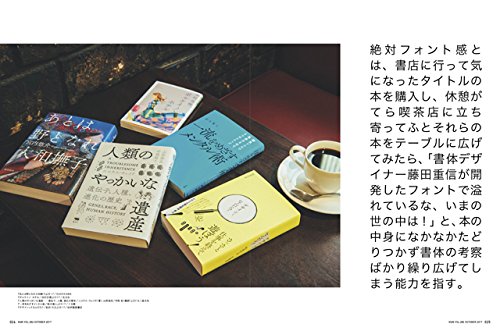
絶対フォント感
文字を見ただけでその書体を言い当てられる能力を指している。
また書店に行って気になったタイトルの本を購入し、休憩がてら喫茶店に立ち寄ってふとそれらの本をテーブルに広げてみたら、「書体デザイナー藤田重信が開発したフォントで溢れているな、いまの世の中は!」と、本の中身になかなかたどりつかず書体の考察ばかり繰り広げてしまう能力を指していたり、端正なフォルムと情感ある墨溜まりで文字好きだったら思わず惹かれてしまう「A1明朝」で組まれたキャッチコピーを見て、そのフェティッシュな書体と言葉の両方からいま映画館で体験できる美しいストーリーと映像を勝手に想像して涙ぐんでしまう能力を指すようだ。いま映画館で体験できるその映画のストーリーに関してはあまり良い評判を聞かないが、果たしてフォントとキャッチコピーだけで涙ぐめるのだろうか。
それはさておき、9月6日に発売された月刊MdN10月号では、一年ぶりに「絶対フォント感を身につける。」が特集され、今回の特集で第3弾となる絶対フォント感を身につける。シリーズでは「明朝体編」がクローズアップされた。
明朝体は縦画が太く横画が細い、また終筆の終わりにうろこがあり、楷書の特徴を残しているといった特徴がある書体。
明朝体編表紙
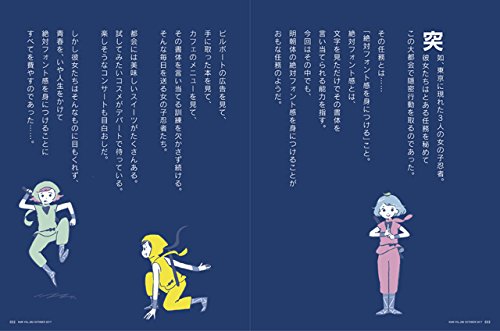
突如、東京に現れた3人の女の子忍者。その任務は「絶対フォント感を身につける」こと。
明朝体の基礎を知る
明朝体の「漢字」は工業製品のような機能美を持っている。これは横画の終筆部分の三角形のうろこの部位など、明朝体におけるフォーマッタブルな部分を説明しての解釈。
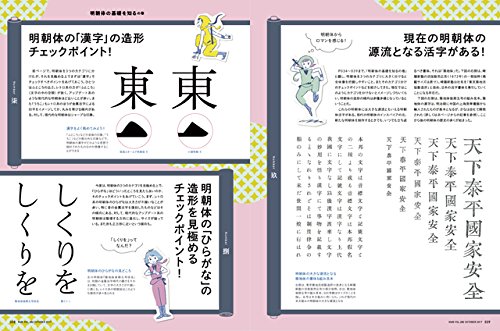
明朝体の「ひらがな」は漢字に比べて体臭がある。漢字に比べて、筆で書かれたような工業化されきっていない部分を説明した文。
游明朝体 Mのはらい
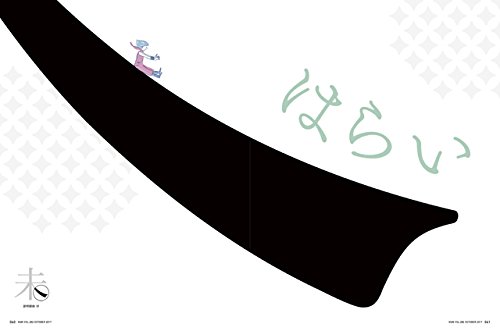
はらいで見開きを使うという贅沢すぎるページ構成。
明朝体の歴史のはじまり。――誰がつくったのか、どう発展したのか
講師:小宮山博史
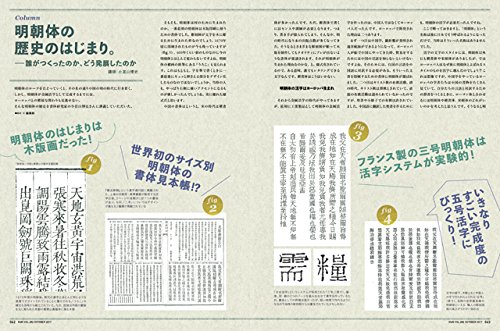
フォント業界のレジェンド・小宮山博史先生による明朝体コラム。
レトロな明朝体を知るの巻
復刻、改刻、インスパイアなどレトロ系明朝体を詳しく解説。
▼游明朝体 Mのはね
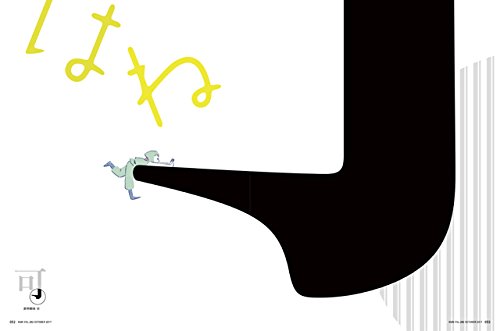
「はね」でも見開きページでぶち抜いてきた!その他にも「うろこ」や「てん」でも見開きを使用してくる粋なページ構成になっていたが、実際問題、結構ページが余ってしまっての決断なのだろうか、少し勘繰りも入る。
クイズ形式で書体名を当てる「世界を旅する!フォント観光大使」
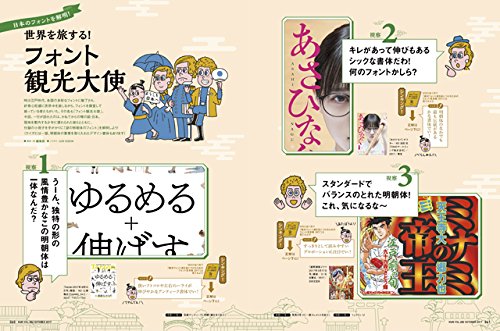
時は江戸時代。各国の多彩なフォントに魅了され、好奇心旺盛に世界中を旅しながらも、フォントを調査して廻っている者たちがいた。その名も「フォント観光大使」。今回、一行が訪れたのは、かねてからの噂の国・日本。現地を案内する少年に連れられた彼らとともに、付録の小冊子を手掛かりに「謎の明朝体」を解明しようという設定。
[クイズには一部、明朝体の要素を取り入れたデザイン書体もあります]と注意書きがあったが、視察10「なぜ明朝体ベースのレトロなデザイン書体をファンタジー小説の装丁に使ったのか」で取り上げれていたダイナフォントのロマン輝の事だろう。
ロマン輝使用書体として取り上げられた書籍「不可解の国のアリッサ」
メリッサだと思ったらアリッサだった。視察4「なぜ柔らかで温かみのある明朝体を不穏な雰囲気の短編集の装丁に使ったのか」の記事ではモリサワの大人気書体であるA1明朝を紹介していた。
A1明朝使用書体で取り上げられ書籍「静かにしなさい、でないと」「支配者」
支配者のタイトルではA1明朝を大胆に加工している。A1明朝ではこれほどに大胆に文字を加工しても重心が崩れず可読性が損なわれず読みやすい。また視察9「なぜ複雑な表情を持つ明朝体を建築家のポスターに使ったのか」ではフォントワークスの筑紫Aオールド明朝 Mが取り上げられていた。
筑紫Aオールド明朝 M使用書体で取り上げられた「村野藤吾の建築 模型が語る豊饒な世界」
ベーシックな明朝体を知るの巻
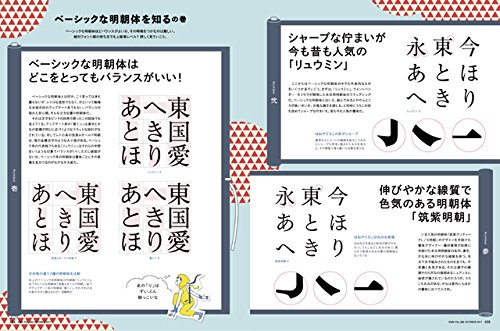
「リュウミン」「筑紫明朝」「本明朝」「イワタ明朝オールド」などを例にオーソドックスな明朝体を開設。
アップデートされた明朝体を知るの巻
「ヒラギノ明朝体」「小塚明朝」「濱明朝」など時代のニーズに合わせて生まれた新しい用途の明朝体を解説。
明朝体を比べて考察するの巻
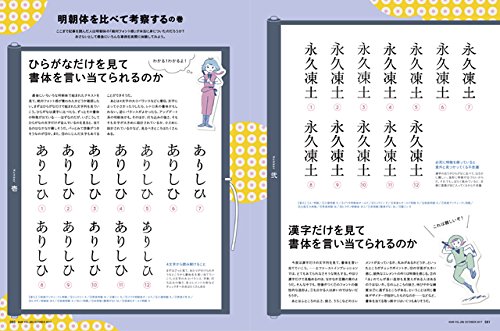
ひらがなだけや漢字だけ、またウエイト違い、組み見本を見て書体が言い当てられるか、しっかりと絶対フォント感が身についたかどうかのおさらいページになっている。
絶対フォント感を身につけるためのフォント見本帳 2017
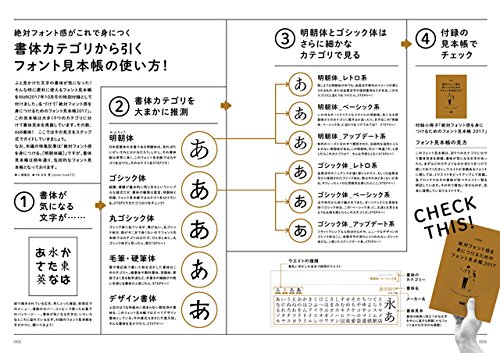
明朝体を特集した2017年版だが、見本帳掲載の書体は明朝体だけでなく、ゴシック体、丸ゴシック体、毛筆・硬筆体、デザイン書体のフォントも網羅。ちなみに明朝体、ゴシック体のフォントはレトロ系、ベーシック系、アップデート系に細分化された分類されて掲載されている。
176ページ、668書体を掲載した「絶対フォント感を身につけるためのフォント見本帳 2017」。付録としては2015年版や2016年版にも付いてきたが今回も2017年版として同梱されている。